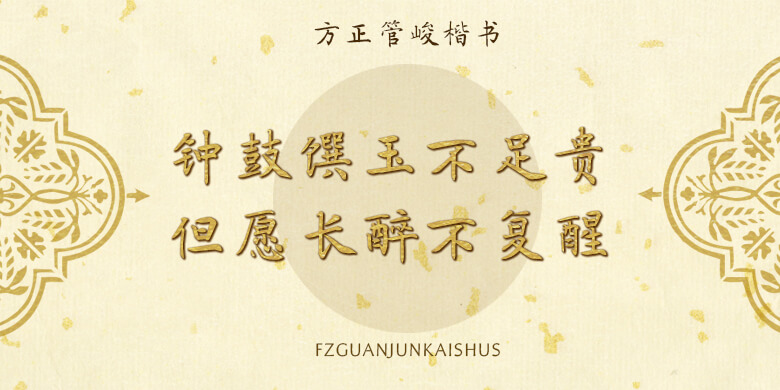
方正管峻楷书
品牌:方正字库设计师:管峻发行时间:2018字库编码:大陆简体(GB2312-80)、简繁扩展(GBK)分类:常规书写·毛笔
方正管峻楷书
管峻楷书由当代书法家管峻先生创作。这款字体用笔细劲又多轻重对比,轻巧自然,结体以褚遂良书法为本,参以己意自成一家,工稳清丽。其风格秀美空灵,适用于文化类的宣传设计,以及商业类品牌的广告和产品包装设计。